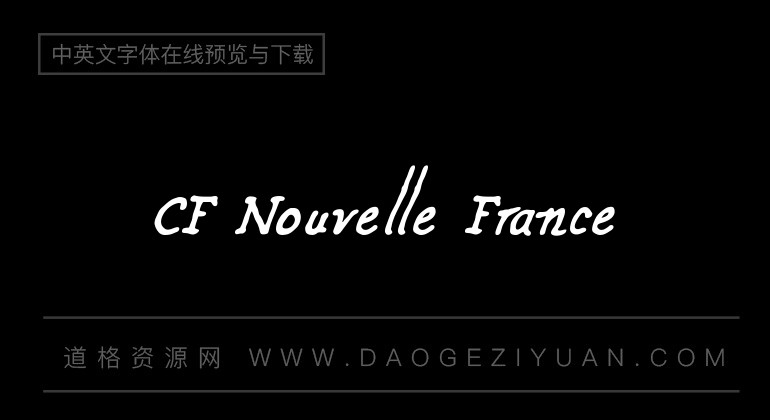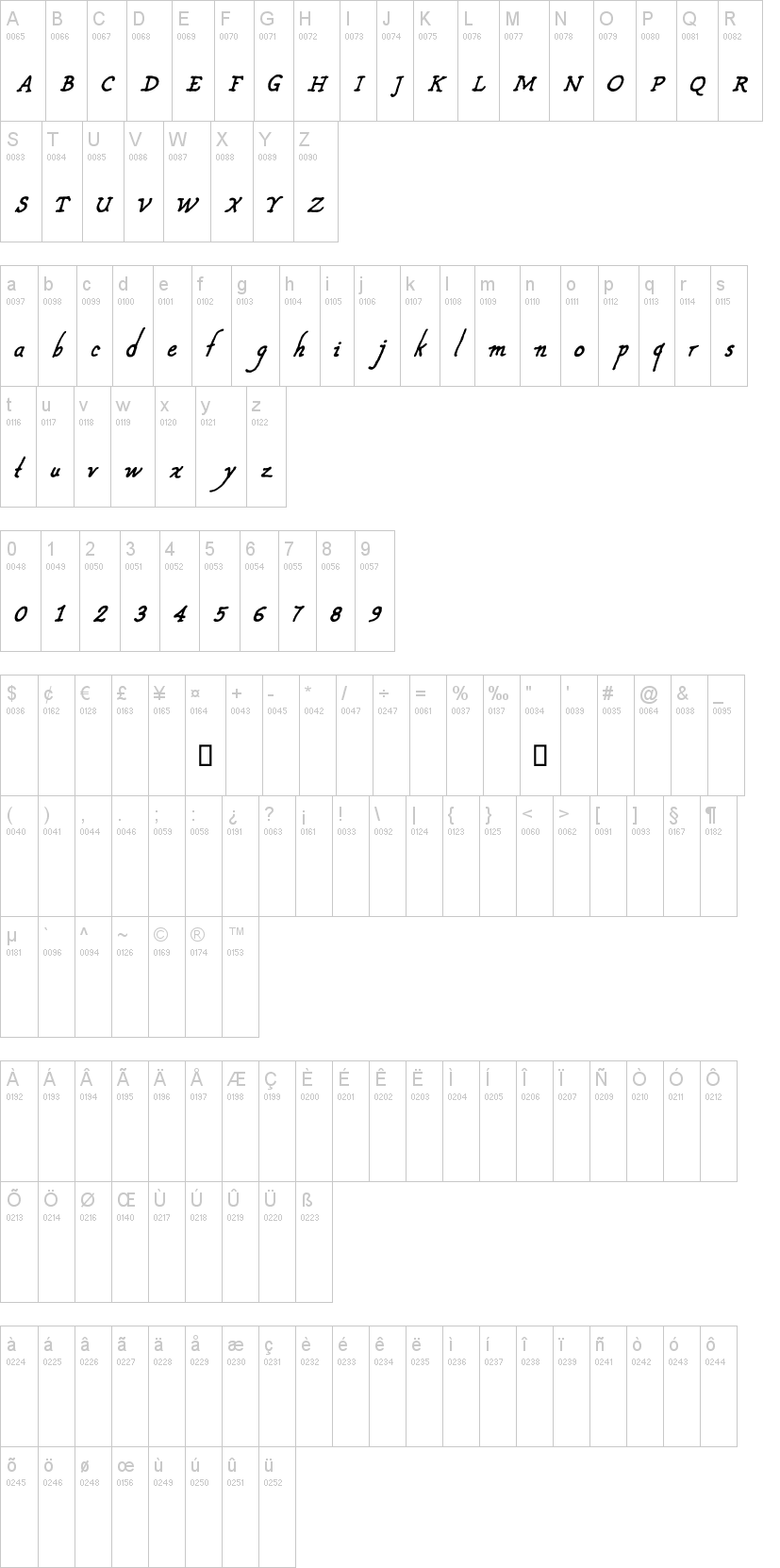
CF Nouvelle France 是一款由 Charles Daoud 创作的现代欧洲字体。它的特点是有着简洁的线条,优雅的字形,以及柔和的曲线。它的字体比例很均衡,非常适合用于报纸,杂志,书籍,网站和其他印刷品。它也可以用于制作照片,图标,标志,海报和其他设计作品。CF Nouvelle France 具有多种字体风格,包括细体,粗体,斜体,衬线和粗斜体,可以满足不同的设计需求。内容介绍
CF Nouvelle France是一款非常不错的手写艺术字体,具有很好的视觉感,适合于文化类的宣传设计、商业类品牌的广告和产品包装设计以及个性化文字排版等较多场景。